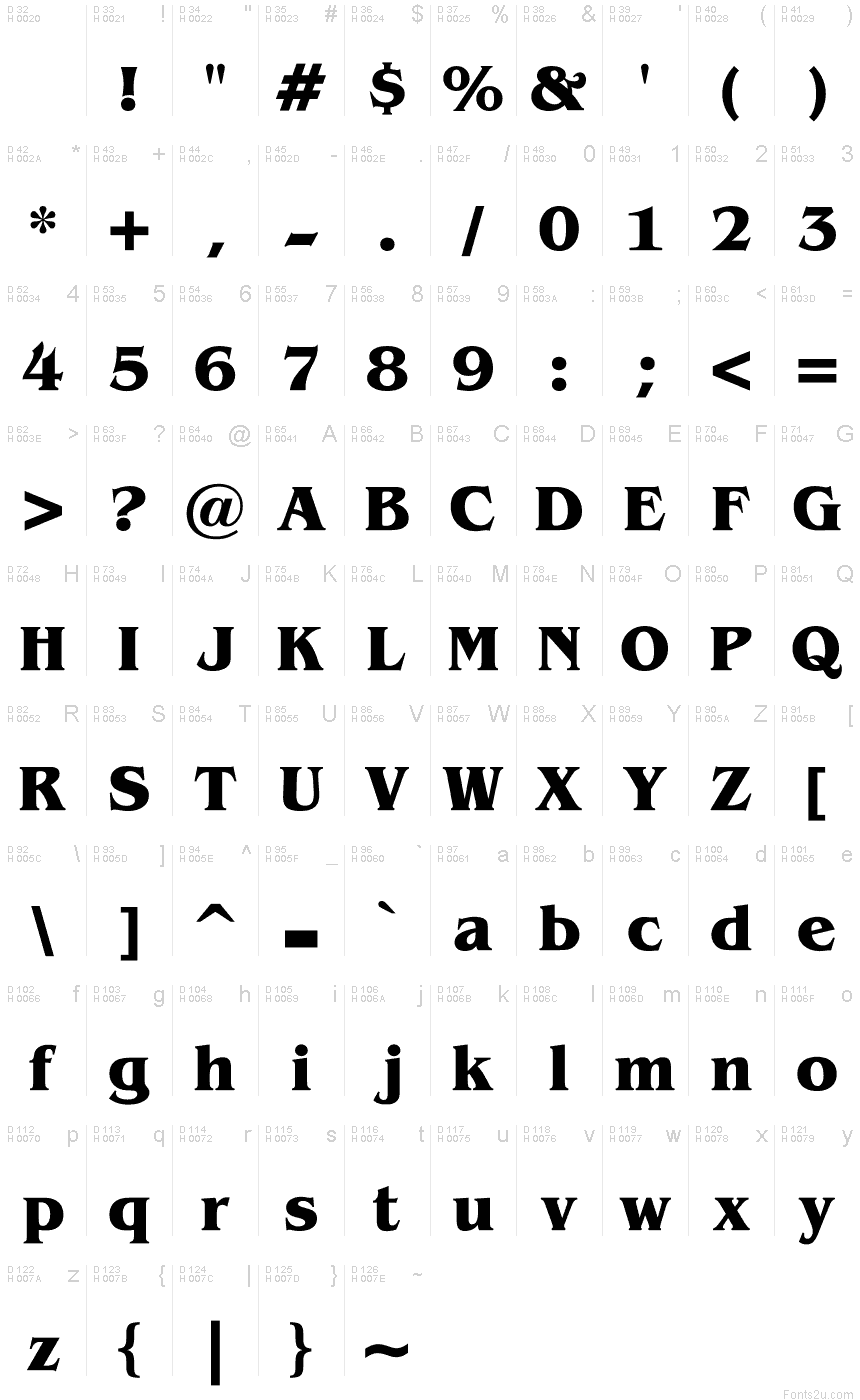
UKIJ Esliye Qara od Uyghur Computer Science Association to darmowy krój displayowy typu „caps serif”, utrzymany w klimacie dawnych plakatów i rzeźbionych liter. Litery łączą szerokie, klasyczne proporcje z ostrymi łączeniami i wycięciami w kształcie kropli. Dzięki temu font sprawia wrażenie dostojnego i lekko dekoracyjnego, nie popadając przy tym w sztywną formalność.
Świetnie sprawdza się w nagłówkach, na okładkach książek, plakatach kulturalnych, planszach tytułowych i monogramach, gdzie potrzebny jest efekt grawerunku i klimat dziedzictwa. Jako darmowy font, idealnie nadaje się do krótkich tytułów, logotypów i nazw na opakowaniach – zwłaszcza gdy chcesz, by wielkie litery przyciągały wzrok dekoracyjnymi wcięciami i masywnymi szeryfami.